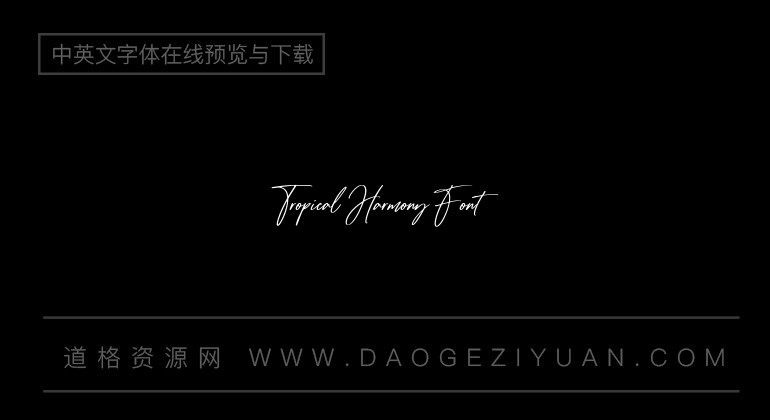
Tropical Harmony Font 是一种非常独特的字体,它的设计师来自印度尼西亚。这种字体的设计风格非常适合用于一些有热带风情的场景,例如海滩、度假村、夏季音乐节等等。 这种字体采用了手写风格的字形,字母间的间隔非常宽松,从而使得整个字体非常的轻松、活泼。字母形状流畅,具有良好的可读性和视觉吸引力。 此外,Tropical Harmony Font 还包括了大量的特殊字符和装饰元素,例如波浪线、叶子、花朵等等,可以让设计师在排版时更加灵活,创造出更加有趣的效果。 总之,Tropical Harmony Font 是一种非常适合用于热带风情场景的字体,它具有非常好的可读性和视觉吸引力,值得一试。内容介绍
Tropical Harmony Font是一款非常不错的手写艺术字体,具有很好的视觉感,适合于文化类的宣传设计、商业类品牌的广告和产品包装设计以及个性化文字排版等较多场景。